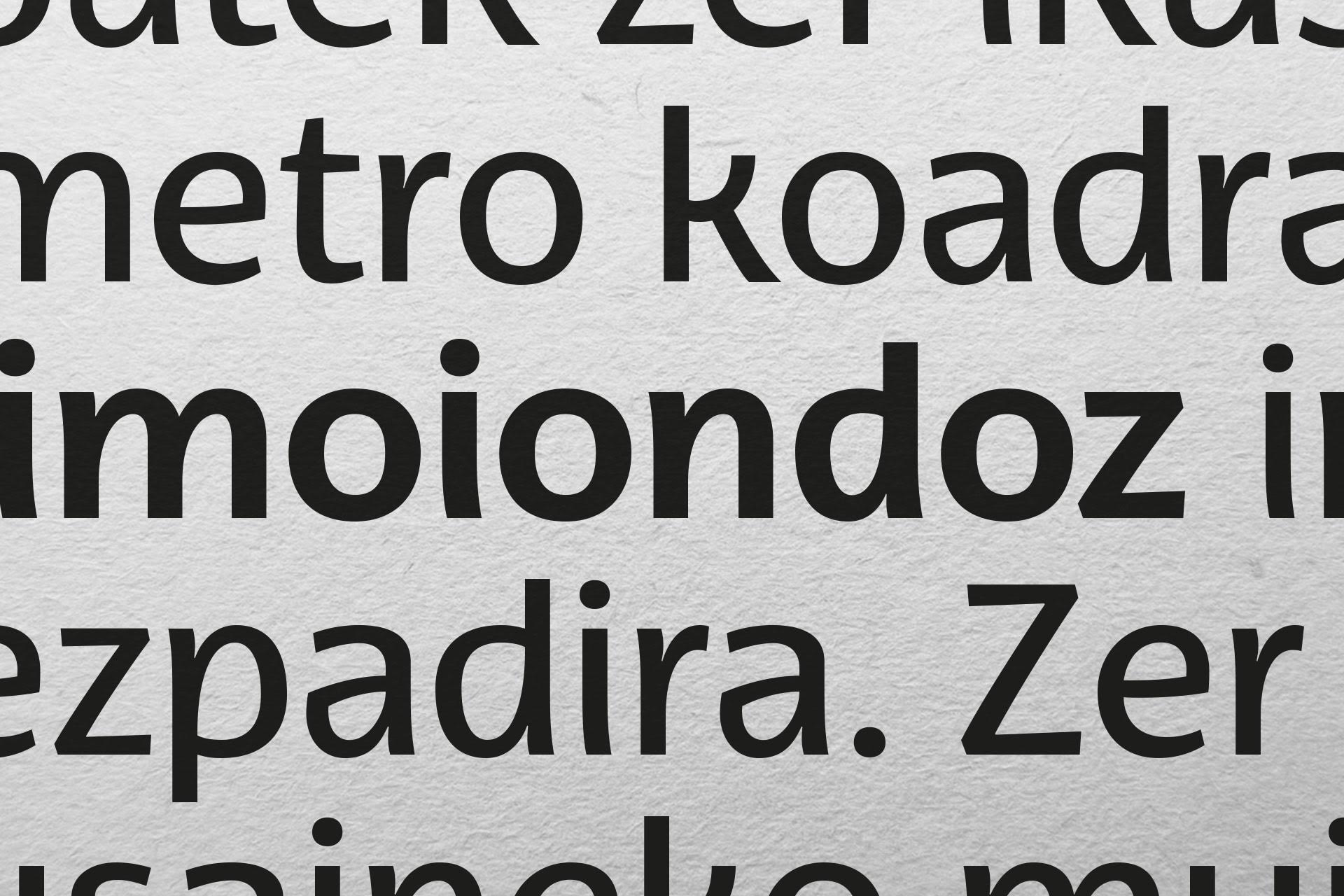
La fuente tipográfica EHU es el resultado del proyecto de investigación desarrollado por el grupo Letraz de la universidad. Contar con una tipografía propia refuerza la identidad de la EHU
El grupo Letraz de la Facultad de Bellas Artes partió para el diseño de la fuente EHU de la conceptualización de la obra de Chillida, en la que encontró conexiones con fundamentos de la tipografía, como son el espacio y la estructura.
La tipografía EHU…
...transmite carácter
Una forma de ser, un estilo, idioma y cultura, nuestros orígenes, nuestra historia, nuestras raíces y nuestro futuro. Creada por y para la EHU, desde dentro hacia el mundo.
...es IMPULSO
Energía, motivación. Un proyecto ilusionante con una meta clara: reforzar nuestra propia identidad.
...es COMPROMISO
La apuesta por unificar nuestros textos con una voz única y propia es firme, sólida y responde a una idea común: dar valor a todos los elementos que trasladan nuestra identidad, porque todos ellos crean la marca EHU.
...es VITALIDAD
Nada refleja tanta vida como las cosas en movimiento. Este proyecto es una muestra más de la capacidad innovadora de la EHU y de su propósito de seguir dando y difundiendo, buscando un futuro mejor.
...es ORGULLO
La fuente EHU es la universidad, su gente, sus proyectos, su aportación a la sociedad. Es un reflejo de nuestro espíritu tenaz. La EHU es una de las pocas universidades del mundo que cuenta con una tipografía propia y esto, además de motivo de orgullo, nos anima a seguir trabajando en esta línea de superación constante.